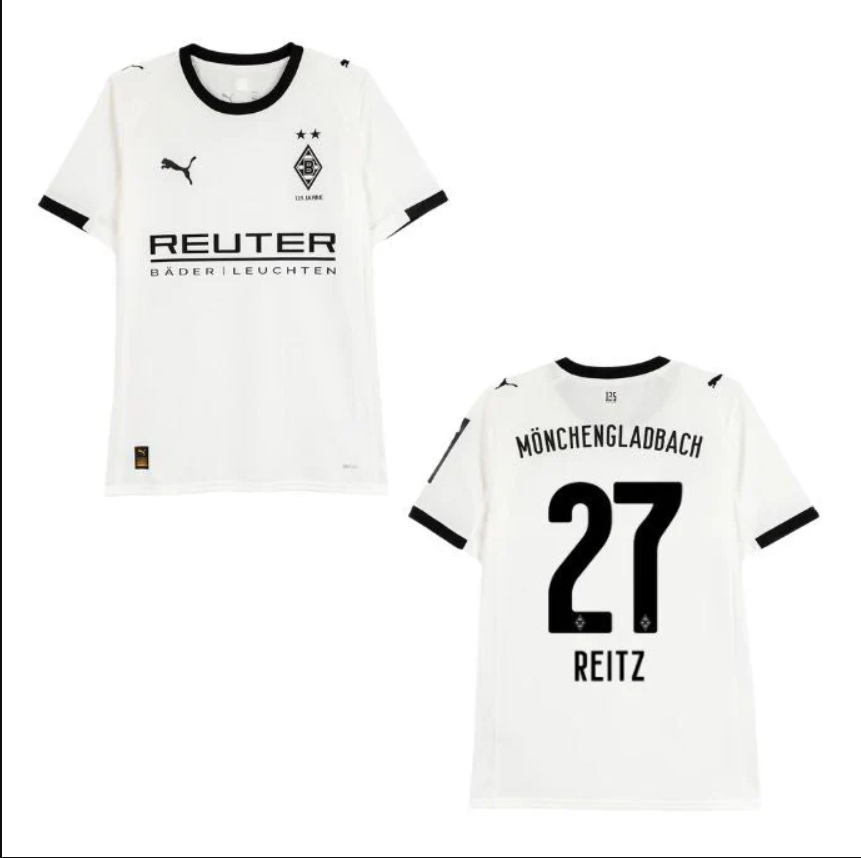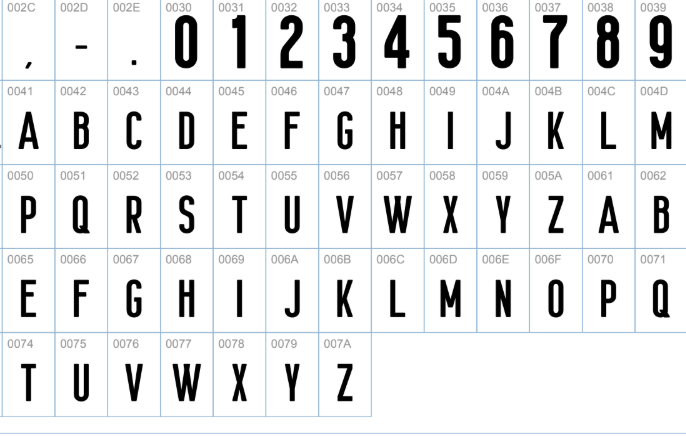
A tradição do futebol alemão encontra o design moderno. Para a temporada 2025-2026 da Bundesliga, a Puma e o Borussia Mönchengladbach apresentam uma identidade visual renovada, mantendo a essência dos “Die Fohlen” (Os Potros).
Estilo Visual e Aplicação
A tipografia desenvolvida pela Puma para o Gladbach nesta temporada aposta em um visual limpo e contemporâneo. O design reflete a precisão da engenharia alemã, com caracteres de peso médio e contornos bem definidos.
Diferente de fontes mais ornamentadas, esta tipografia prioriza a legibilidade rápida em campo e na TV. Os números possuem cortes angulares sutis que dialogam com o logo da Puma, criando uma harmonia perfeita tanto na camisa branca clássica quanto nos uniformes alternativos. É uma fonte que transmite estabilidade e força, ideal para destacar nomes de jogadores lendários ou personalizados.